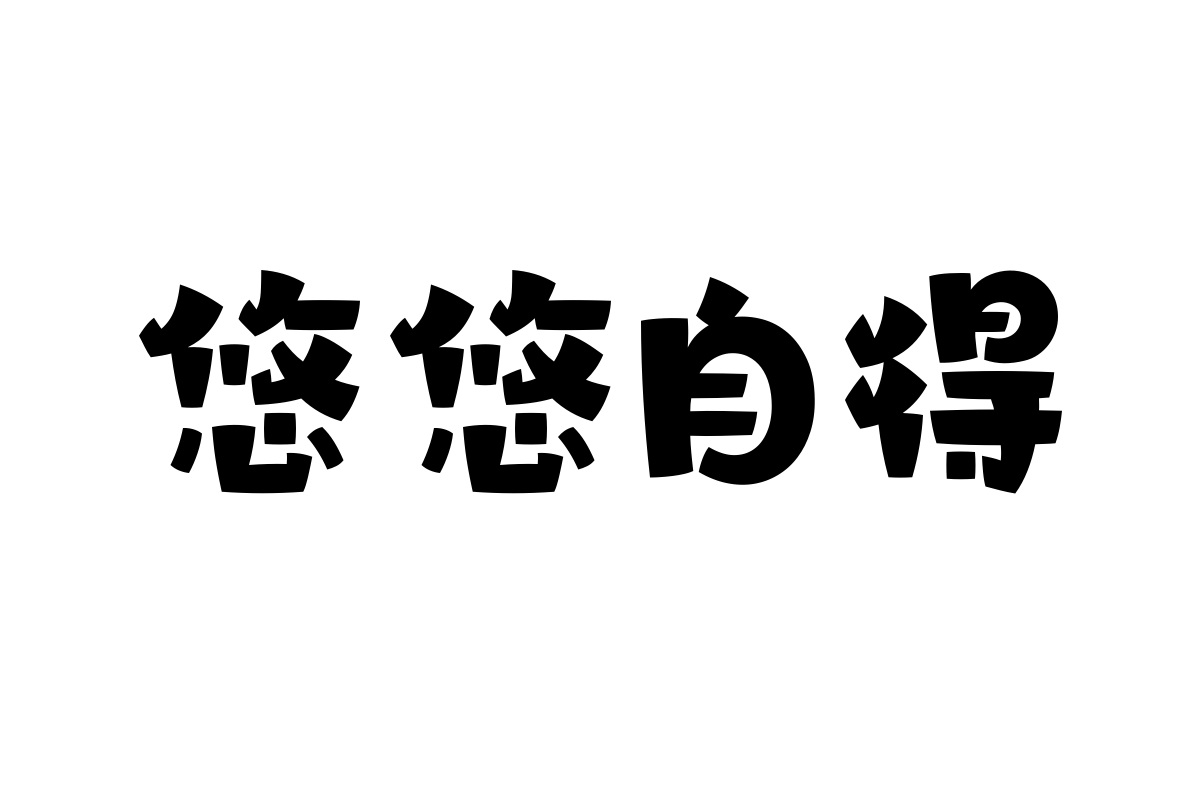
汉仪铸字妙想繁体字体是一款由汉仪公司开发的汉字字体软件,具有独特的艺术风格和设计感。这款字体采用了现代的设计理念,将传统书法与现代平面设计相结合,创造出独特的视觉效果。它适用于各种商业、广告、设计等领域,能够为设计师提供丰富的创意灵感。
汉仪铸字妙想繁体字体的特点包括:
1. 独特性:汉仪铸字妙想繁体字体具有独特的艺术风格和设计感,与其他普通字体相比更具特色。
总之,汉仪铸字妙想繁体字体是一款功能强大、易于使用且具有独特风格的字体软件,适合各类设计师使用。